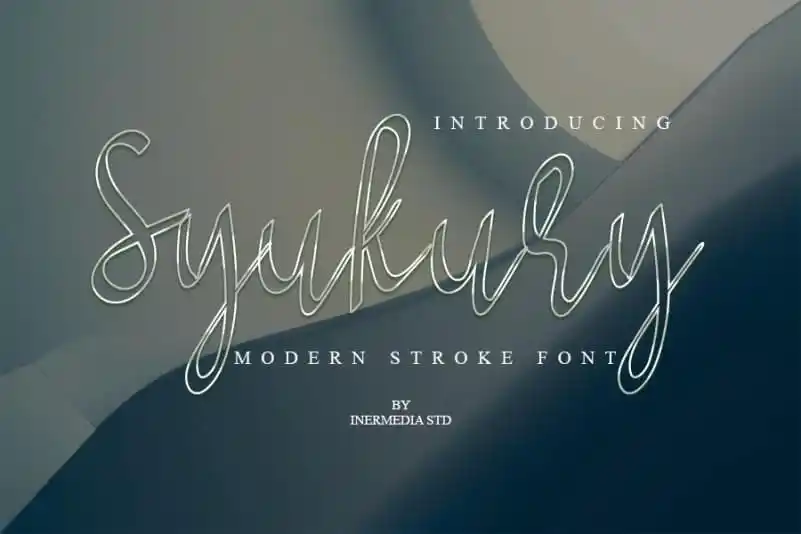
Sukury Script Font é uma elegante fonte de calligrafia ideal para quem busca uma mão escrita delicada em suas criações digitais. Desenvolvida por inermediaSTUDIO, este estilo único e sofisticado encaixa-se perfeitamente em design gráfico que requer uma aposta em um toque humano. Suas linhas são fluidas e detalhadas, criando um efeito vibrante em quase qualquer projeto – desde cartões de agradecimento e convites nupais até logotipos e cards de negócios. Sukury Script é um recurso essencial para quem busca manter seu design gráfico com uma escrita autêntica e única, que transmite um toque personalizado em qualquer projeto.